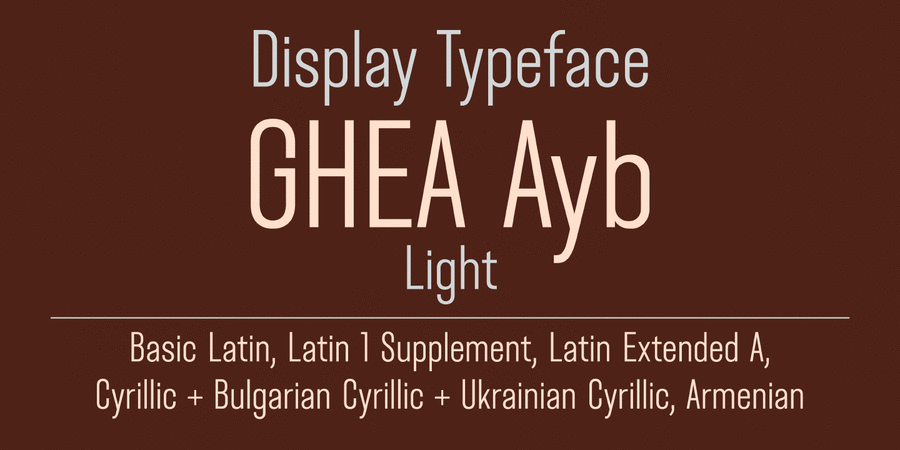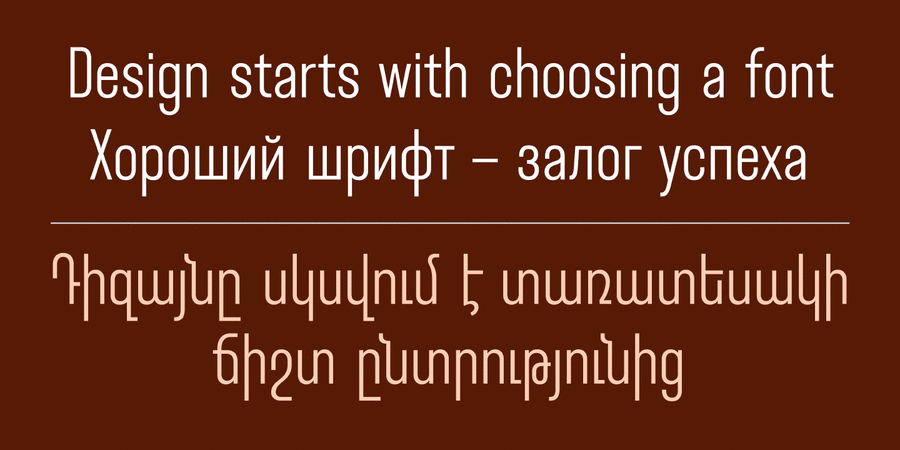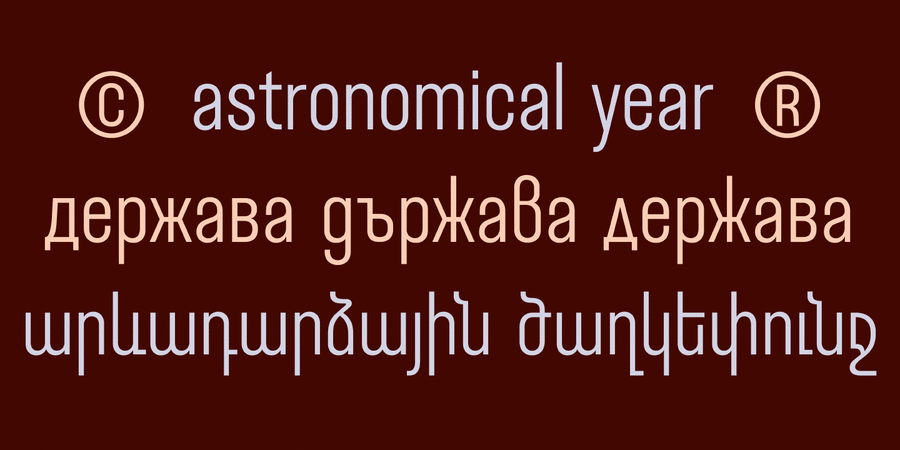
Цей вузький акцидентний гротеск може використовуватися в назвах, заголовках і коротких текстах. Ayb підтримує розширену латинку, кирилицю, включно з українськими та болгарськими варіантами літер, а також вірменську абетку. Шрифт розробив Едік Габузян у 2020 році.
Особливості сімейства шрифтів GHEA AybХіт десятиліття:
Асоціації з сімейством шрифтів GHEA AybОсобистість і характер гарнітури:
точний, рівний, прямокутний, стабільний, стійкий, стрункий, статичний, міський, урбаністичний, розумний, високий